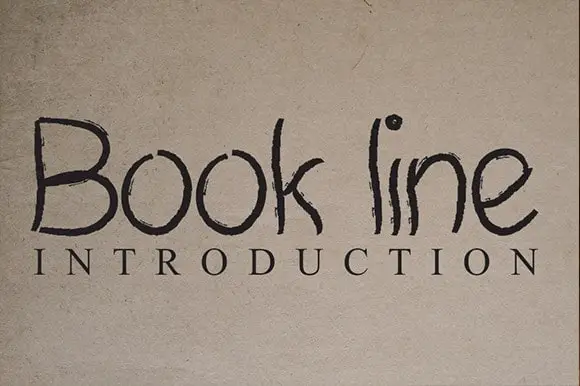
Book Line Handwritten Font
A Book Line Handwritten Font é perfeita para quem procura uma fonte elegante e delicada que transmite sabor e personalidade. Suas linhas suaves e desenhos cuidadosamente pensados são ideal para estilos modernos, combinando com designs de parede, anúncios, postagens nas redes sociais, embalagens de produtos, identidades digitais e até mesmo em fotografias. Esta fonte é versátil e adaptável para uma variedade de projetos que buscam um toque delicado e encantador. Seja você um designer ou artista digital, a Book Line Handwritten Font oferece-lhe a oportunidade de criar designs únicos e memoráveis, sejam eles identidades digitais, anúncios em impressão ou até mesmo embalagens personalizadas. Com sua caligrafia delicada e seu design exclusivo, esta fonte é ideal para qualquer projeto que busque uma combinação perfeita de sofisticação e estilo pessoal. Em um mundo onde cada detalhe conta, a Book Line Handwritten Font se destaca por ser uma opção confiável para aqueles que procuram uma fonte que expressa sentimentos únicos e atemporais. Ela é a escolha perfeita para quem busca transparência em design, oferecendo um toque autêntico que se integra de maneira elegante ao seu projeto.